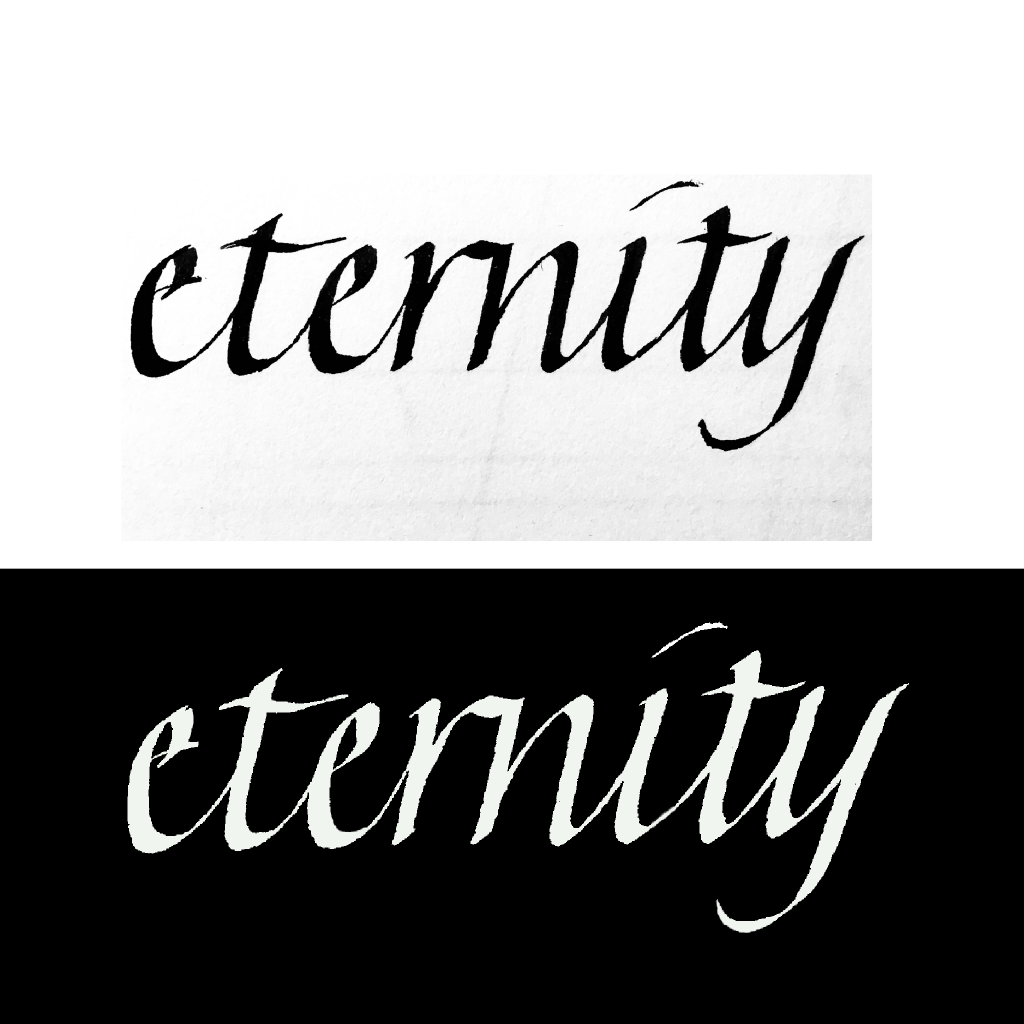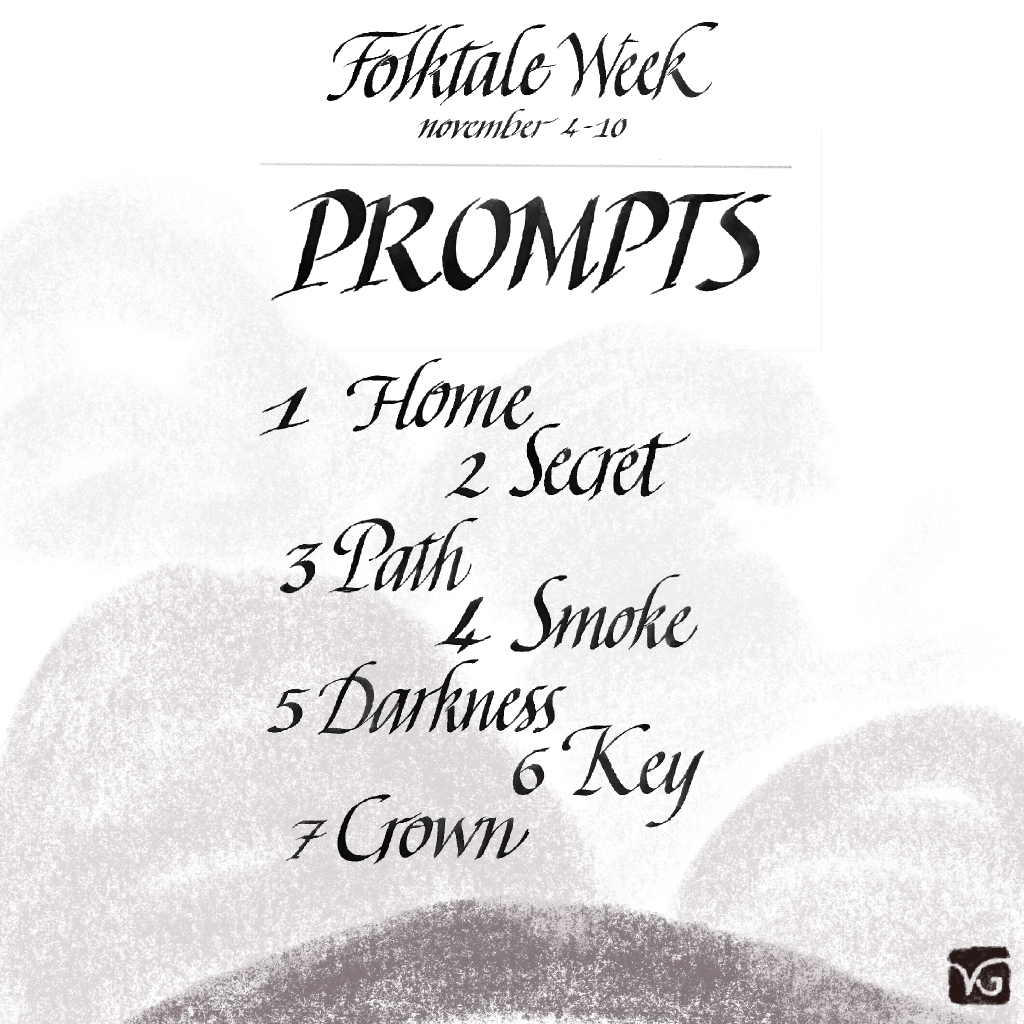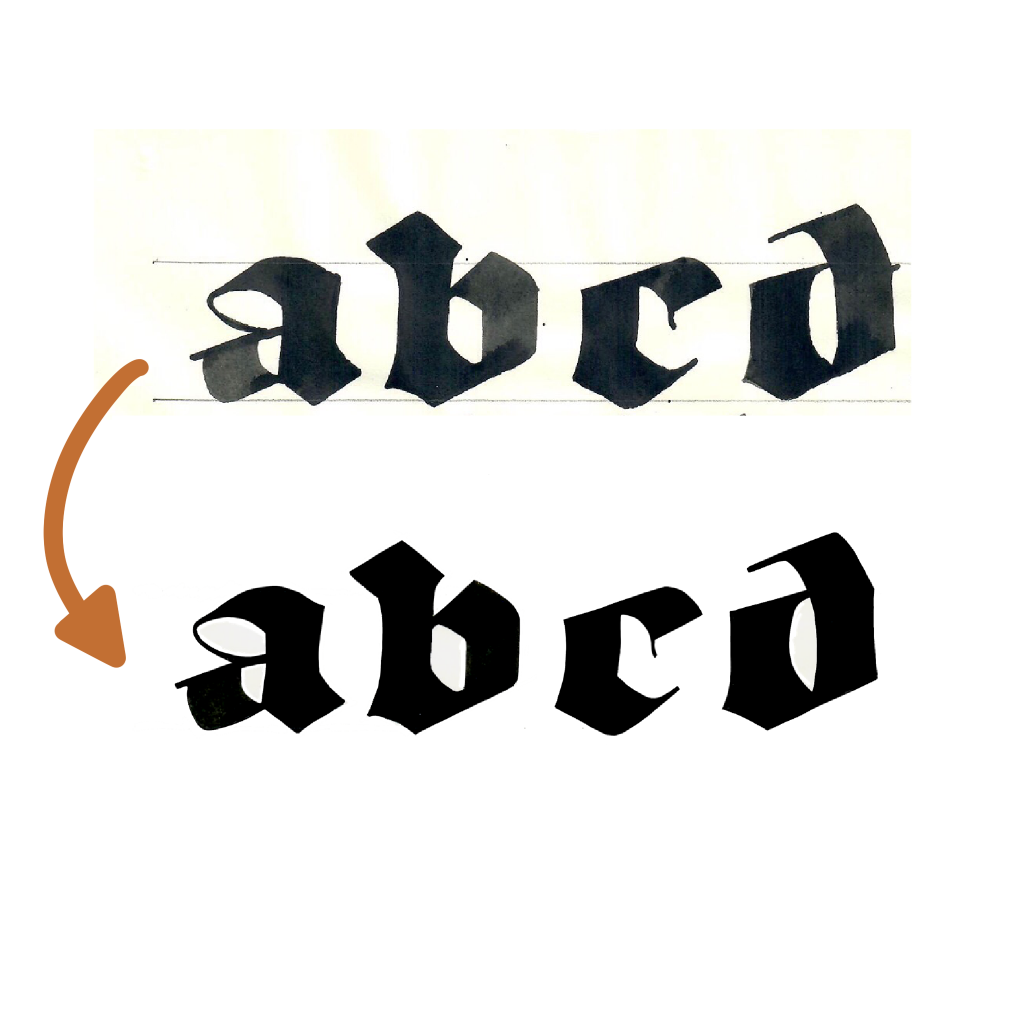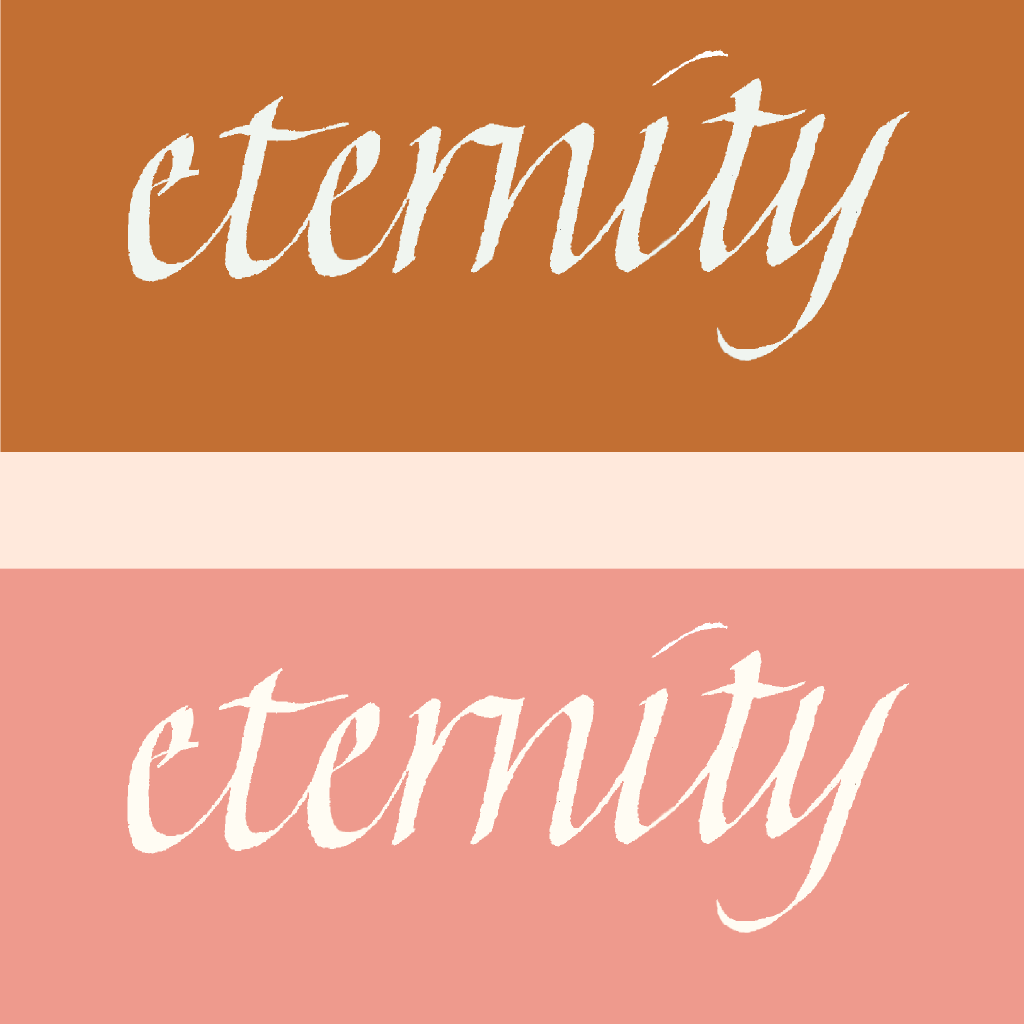
Bien que travaillant principalement sur papier avec des outils traditionnels, de la peinture et des encres, j’utilise aussi largement les outils numériques. Je propose de vous présenter ce que j’utilise et pour quoi faire, en commençant par les outils sur Ipad. J’ai un Ipad 2 depuis quelques années, qui peut être utilisé avec l’Apple Pencil. C’est sans hésiter l’outil dont je me sers le plus, quotidiennement.
Ce n’est pas la version Pro de l’Ipad, beaucoup plus chère, mais l’écran est suffisamment grand pour moi et je fais tout ce que je veux avec.
Mes outils sur Ipad
Procreate
Pour dessiner, coloriser, nettoyer/retoucher des images scannées, tester des compositions, Procreate est mon outil de prédilection. Peu cher (10€), super simple à prendre en main, c’est vraiment l’app à avoir.
Je n’utilise que très peu des nombreux pinceaux qui existent et j’ai acquis pour pas cher le set “Bardot Gouache” qui propose des textures de pinceau plus intéressantes que le set de base. Il existe pleins de sets pour l’aquarelle, et même des stylets calligraphiques (que j’ai testés mais je ne suis pas fan du tout).
Comment j’utilise Procreate ?
Pour tester une composition : très pratique pour bouger et redimensionner les éléments d’une composition en quelques coups de stylets, on peut aussi tester les couleurs à l’infini.
- Soit je scanne (ou je prends en photo) mes brouillons et je les découpe dans l’application pour les arranger
- Soit je griffonne le brouillon directement sur l’app avec le stylet, mais c’est plus rare.
Pour créer des visuels à imprimer, ou pour diffuser sur les réseaux sociaux ou sur le blog : pour cela je scanne ma création de base qui est sur papier, et grâce à Procreate je peux recadrer, nettoyer les petites imperfections, changer les couleurs etc.
Pour créer des éléments illustrés “propres”, pour faire des motifs par exemple : je me sers de Procreate pour reporter le dessin au propre, comme pour un calque.
Les limites de mon utilisation de Procreate
Je ne crée jamais à 100% en digital : il y a toujours l’étape papier. C’est ma façon de faire, car je suis plus à l’aise sur papier et surtout j’éprouve beaucoup plus de plaisir. J’ai en effet du mal à ne travailler que sur tablette, car les sensations ne sont pas du tout les mêmes. Je compare souvent le travail 100% digital à la salade en sachet : ça dépanne, mais ce n’est pas aussi savoureux qu’une bonne salade fraiche !
Adobe Photoshop Express
Même s’il y a de base des fonctionnalités de retouche de photos dans l’Ipad, cette app est un cran au-dessus. Fait rare avec Adobe, elle est gratuite pour les fonctionnalités de base. Pour une utilisation plus poussée, il faut payer un abonnement, bien sûr… mais on peut s’en sortir très bien avec la version gratuite.
Si vous avez Photoshop Creative Cloud, vous avez d’emblée accès à toutes les fonctionnalités de l’app, et vos contenus sont synchronisés dans le cloud, donc accessibles sur votre Ipad, votre smartphone, et votre PC.
Comment j’utilise Photoshop Express ?
Pour de la retouche de photo : recadrage, retouche des contrastes/luminosité/netteté, et parfois application de filtres.
Je retouche ainsi quasiment toutes les publications que je fais sur Instagram, car la photo de base est souvent mal cadrée ou sous-exposée.
Les limites de mon utilisation de Photoshop Express
Pour des composition plus complexes, notamment la création de motifs répétitifs ou les maquettes, j’utilise la version PC de Photoshop. L’app est très basique, idéale pour des retouches rapides et du recadrage, mais reste limitée.
De plus pour des arrangements complexes, il est plus confortable de travailler sur un grand écran.
InShot
Inshot est une app gratuite permettant de faire des montages vidéos : donc utile par exemple pour publier des contenus sur le web ou les réseaux sociaux. Très simple d’utilisation, les fonctionnalités basiques et gratuites sont amplement suffisantes pour faire de chouettes vidéos. Comme pour beaucoup d’app, il y a des achats intégrés si on veut aller plus loin.
En général je filme avec mon Iphone, et je peux monter sur InShot en quelques clics, ajouter de la musique, des titres, etc.
Conclusion
Il existe beaucoup d’applications pour Ipad, j’en ai essayé pas mal. Finalement j’utilise principalement Procreate et Photoshop Express pour recadrer, retoucher, calibrer des compositions, tester des mises en couleurs. Autant dire que je ne suis pas du tout versée dans l’art numérique, j’aime trop travailler avec les outils traditionnels. Mais ces outils me sont tout aussi utiles qu’une imprimante/scanner par exemple. C’est une étape pour aller plus loin, et notamment produire des contenus utilisables dans d’autres contextes : cartes à imprimer, logos, motifs à imprimer, publications sur le web etc.
Enfin, j’essaie de ne pas dénaturer la création originale en sur-travaillant sur Procreate ou Photoshop. La calligraphie a du charme lorsque qu’elle a cette touche légèrement imparfaite, et il me parait important de la conserver. Sinon, autant utiliser des typographies toutes prêtes…
Merci Véro pour ce nouvel article ! Comme toi, mon amour du papier, des plumes, des pinceaux et des encres me laisse un petit goût de salade en sachet quand je travaille en numérique, mais c’est vrai que c’est quand même super pratique et l’association des deux fait vraiment gagner un temps fou. Je me souviens dans les années 90, quand on faisait des montages à la photocopieuse, avec du scotch !!! 😅 Ça a quand même bien évolué depuis ! Vive Procreate et Photoshop ! Bisous ♥️